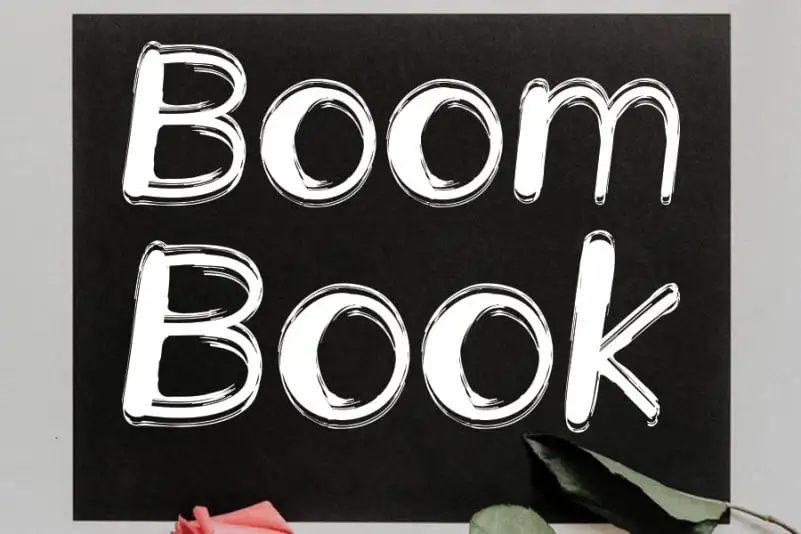
Boom Book Display Font é uma fonte escrita a mão casual e única criada utilizando um pen à esferilla. Esta fonte se destaca pela sua aparência limpa, com um toque de personalidade que faz dela perfeita para aplicações como logomarcas, identidades visuais, redes sociais e projetos DIY criativos. Seus traços levemente curiosos fazem de Boom Book Display uma opção ideal para quem busca algo descompromissado e autêntico em seu projeto visual. Ideal para criar um estilo único que se destaca em qualquer projeto gráfico, a Boom Book Display é uma escolha perfeita para designers buscando incorporar uma pitada de originalidade em suas criações.